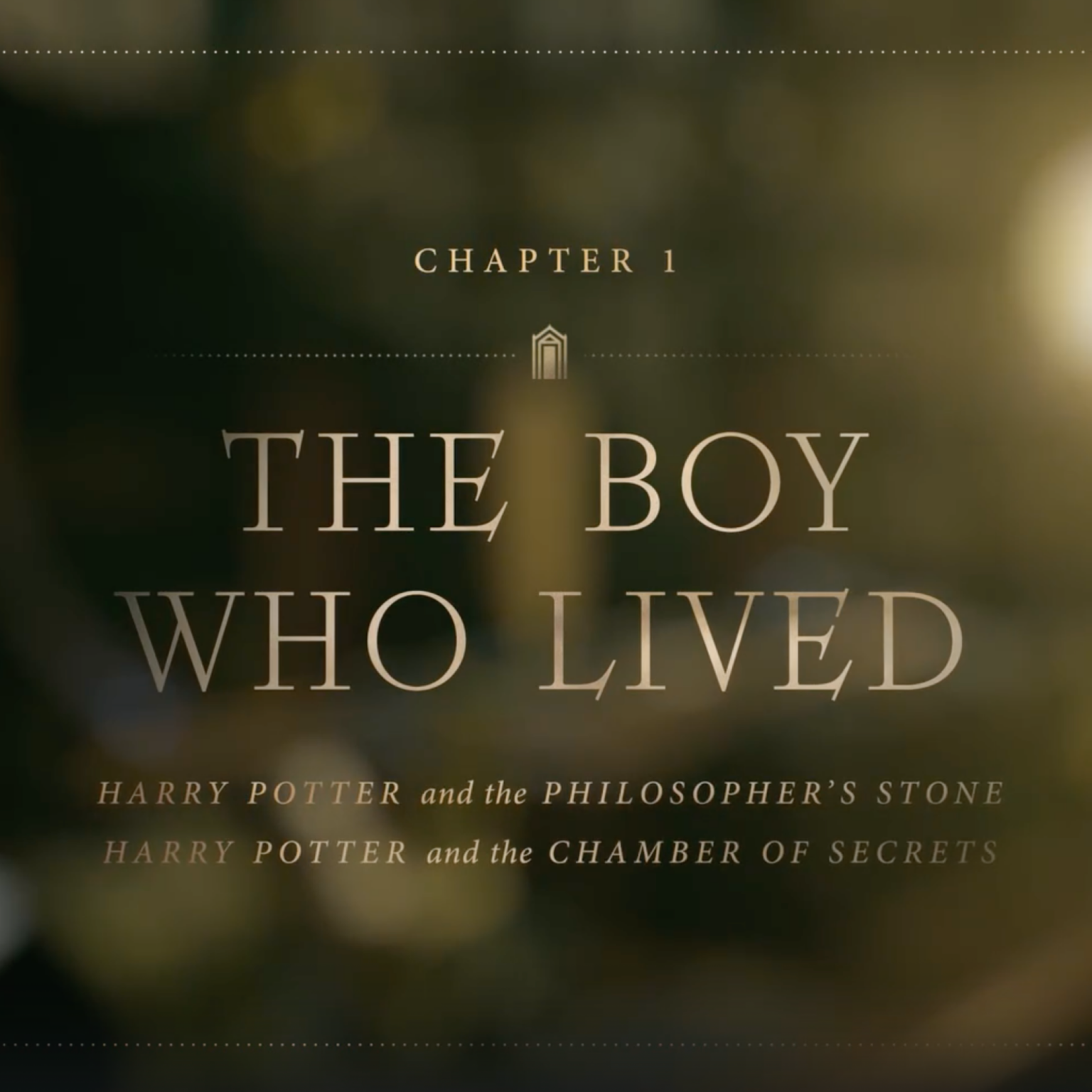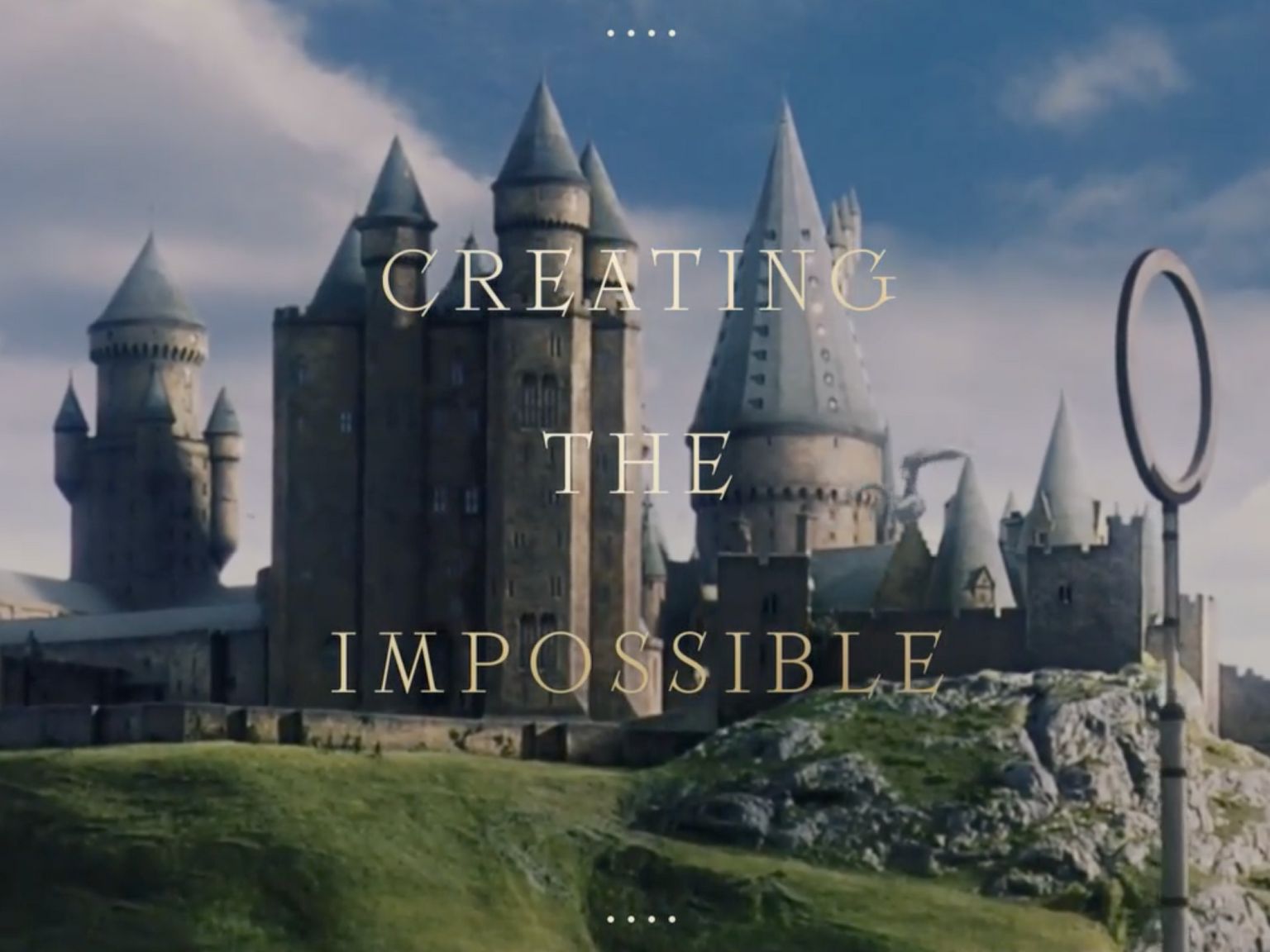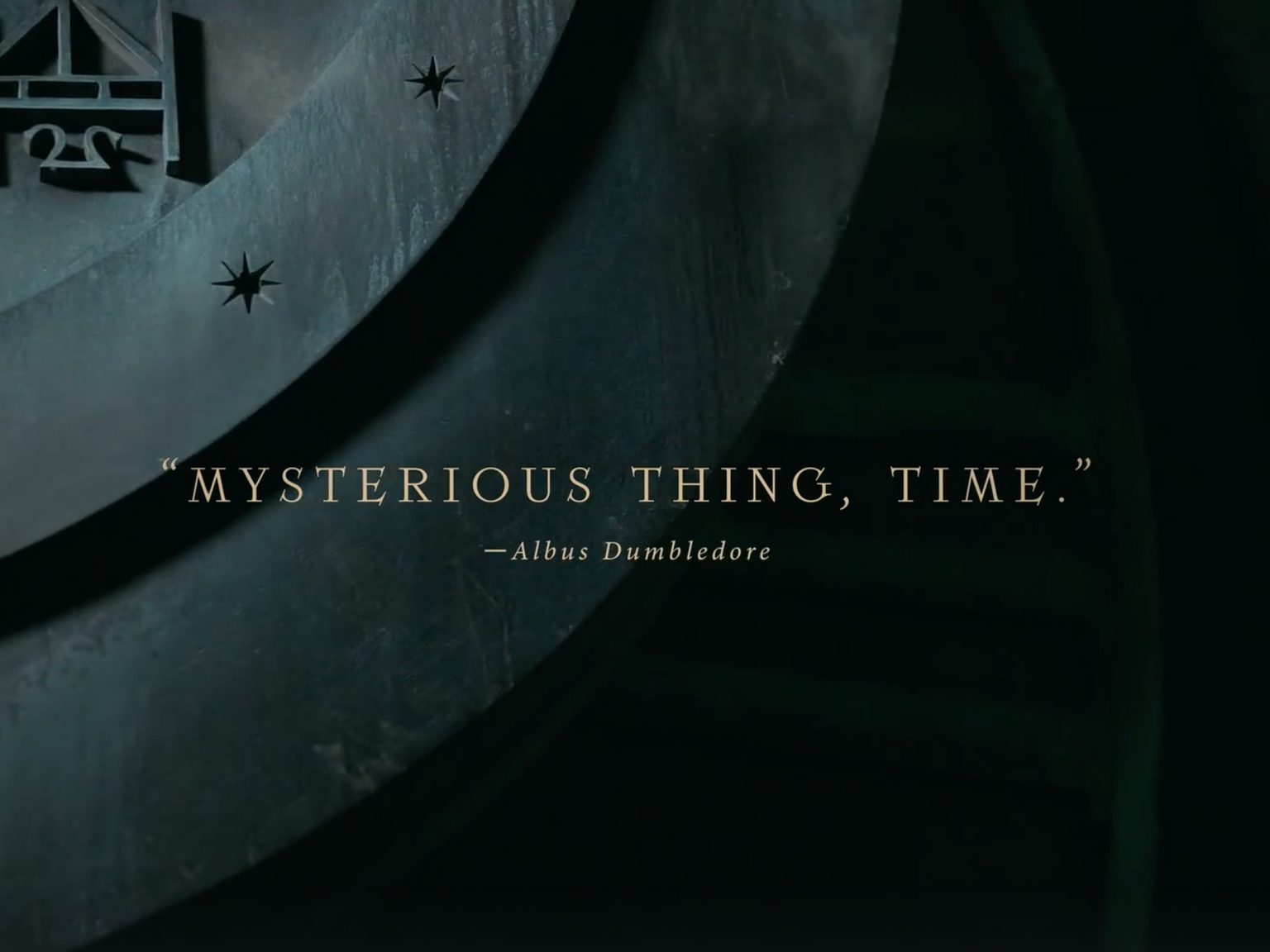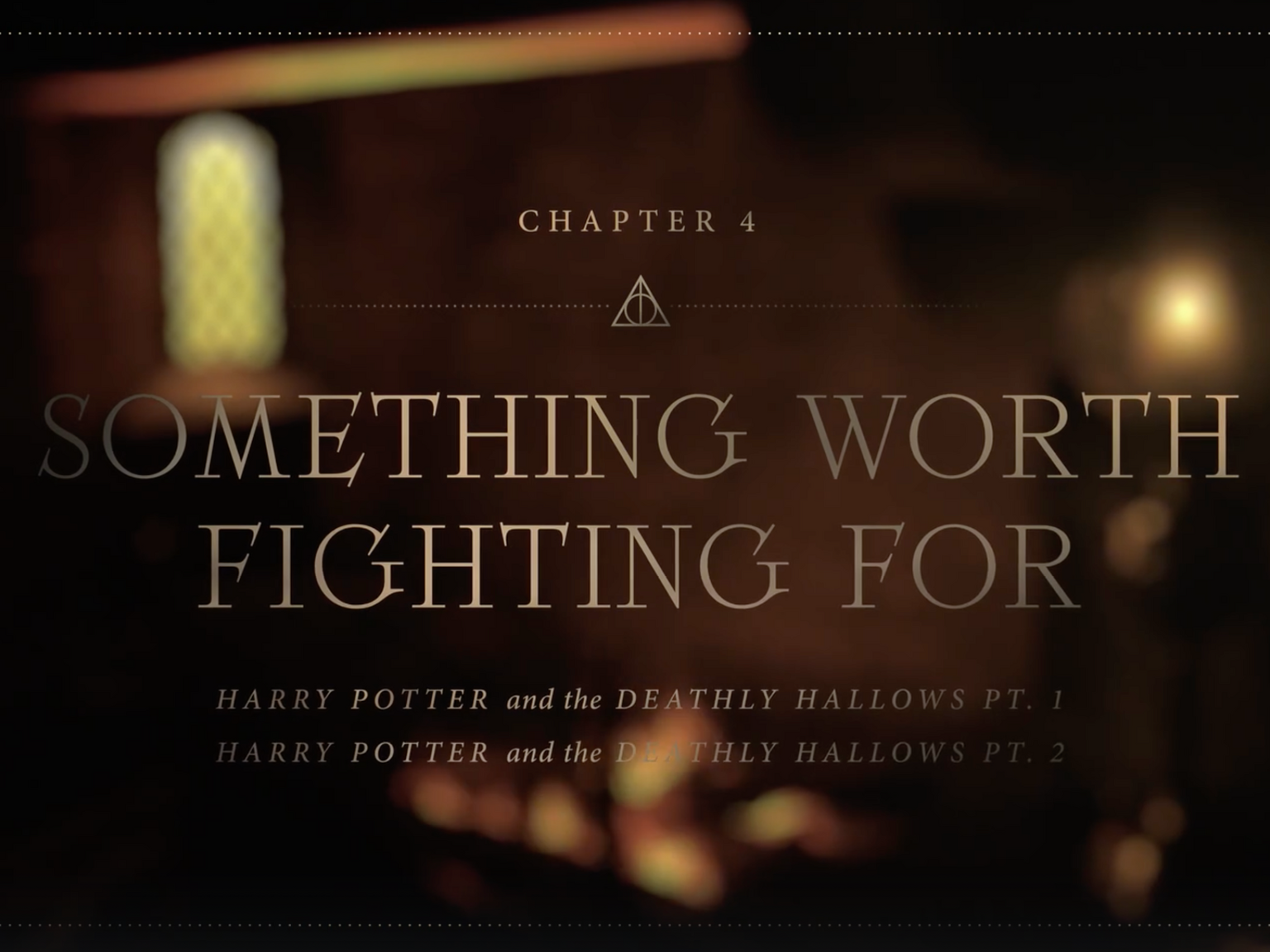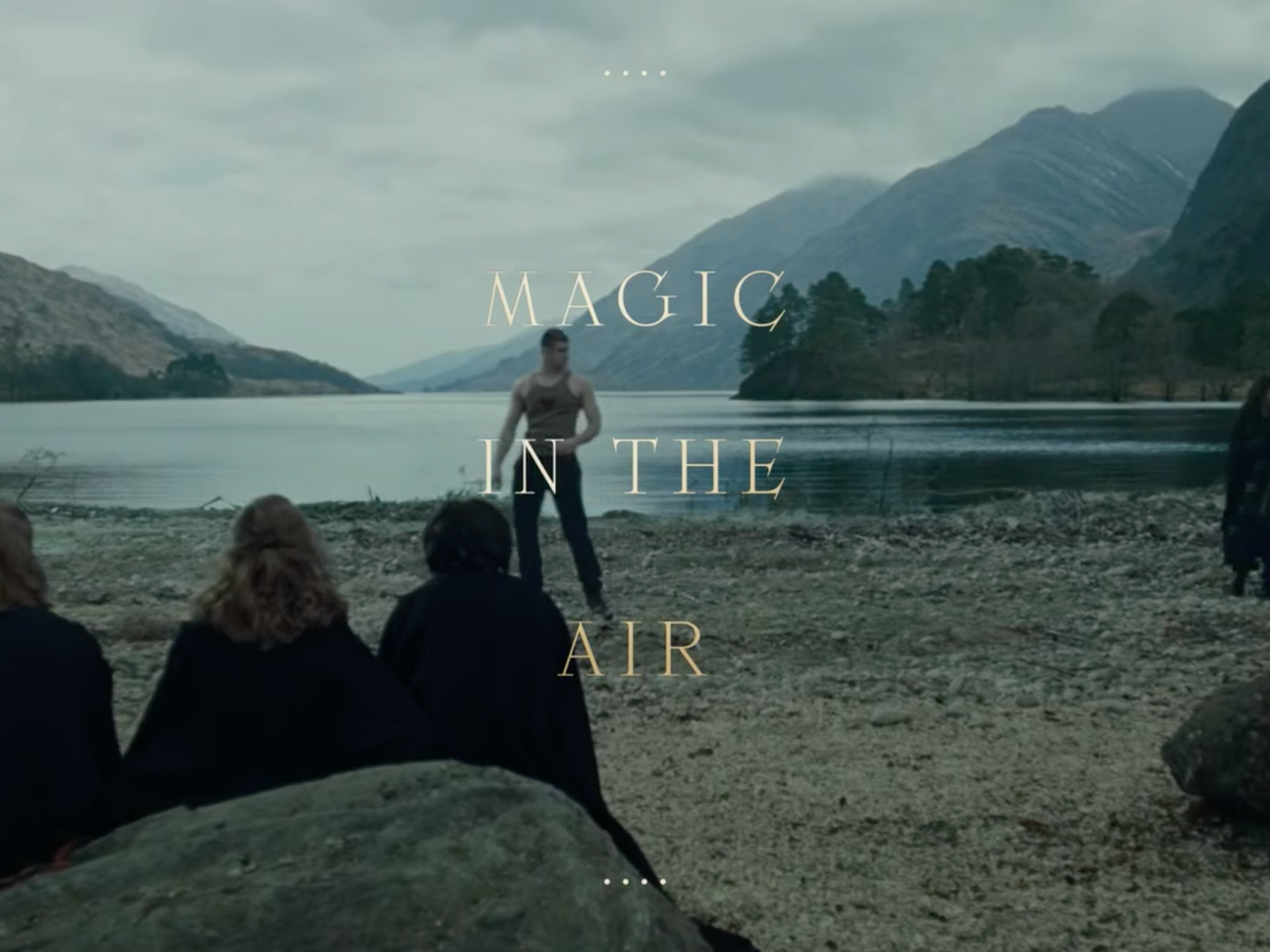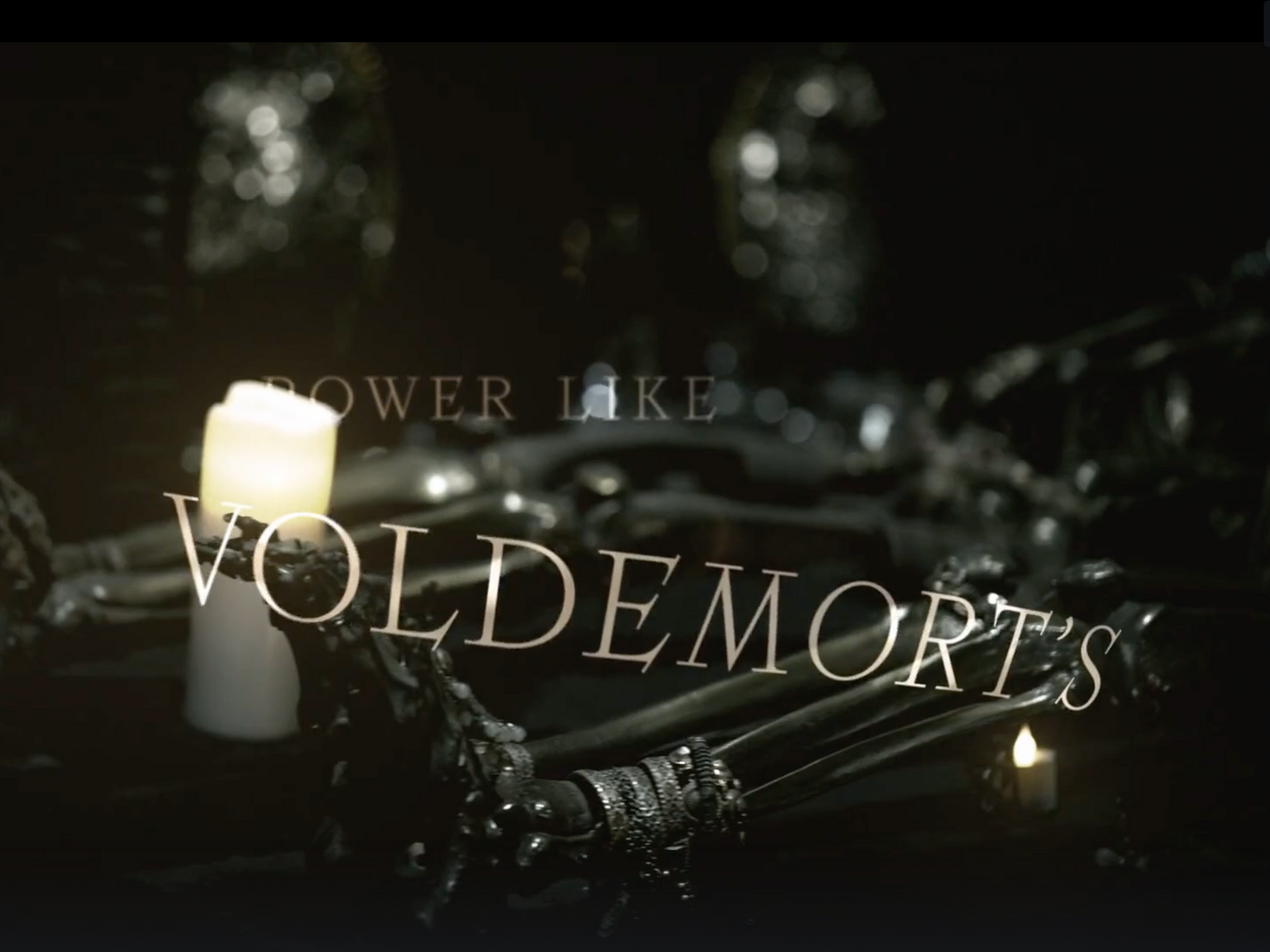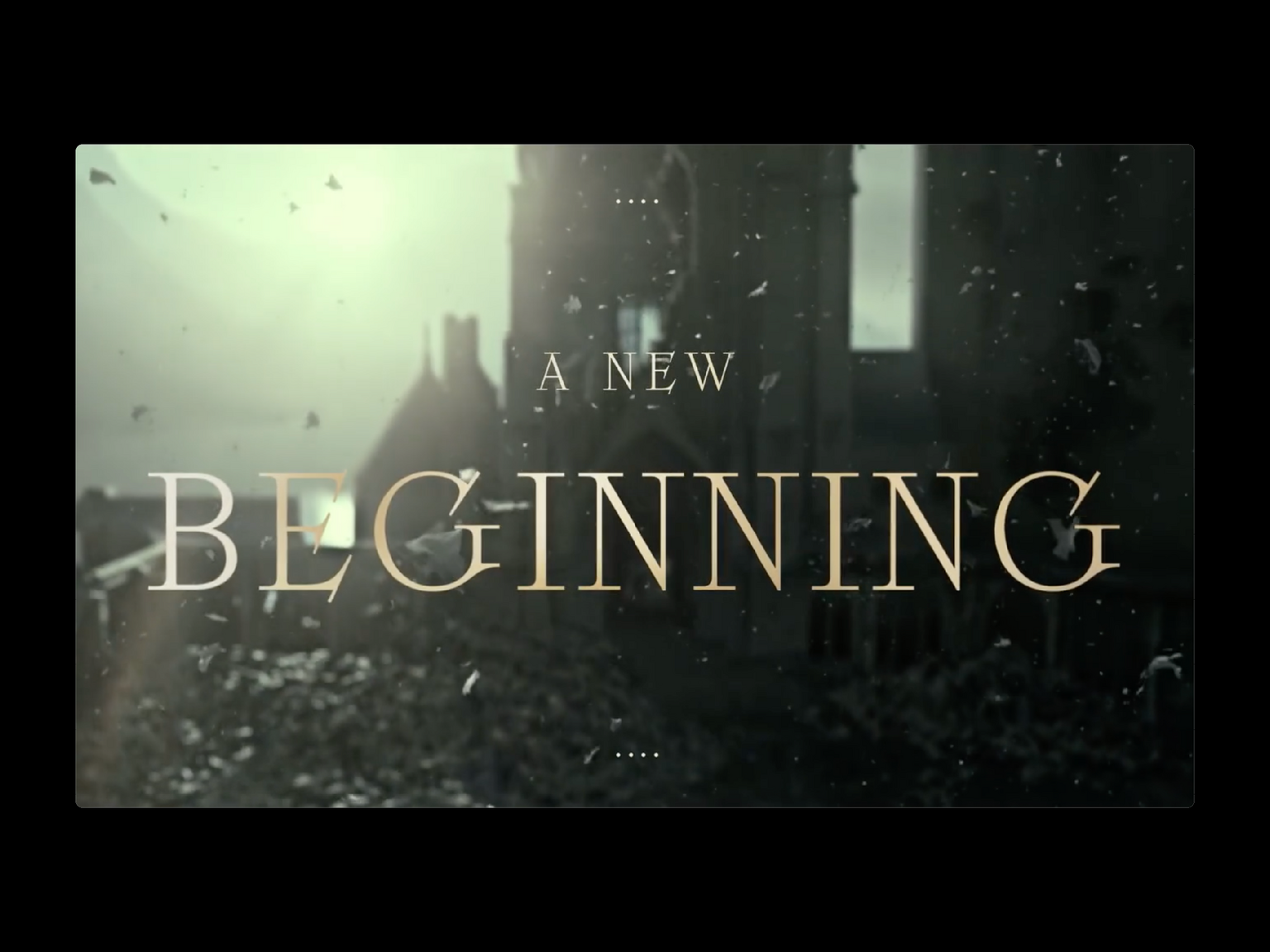
Dieses Jahr erhielten die Fans des Franchise ein einzigartiges Geschenk: die Sonderfolge «Harry Potter 20: Rückkehr nach Hogwarts». Das Wiedersehen mit den Lieblingscharakteren ist bittersüß und nostalgisch, und Clips mit den schönsten Momenten aus dem Film sind überall in den sozialen Medien zu sehen.
Während des gesamten Films sehen die Zuschauer die TT Ricordi Fulmini, in der die Kapitelüberschriften und das letzte Zitat aus dem Buch gesetzt sind. Es handelt sich um eine moderne Antiqua mit historischen Wurzeln, die zur historischen Ästhetik Großbritanniens passt, und TypeType freut sich, ein Teil davon zu sein.